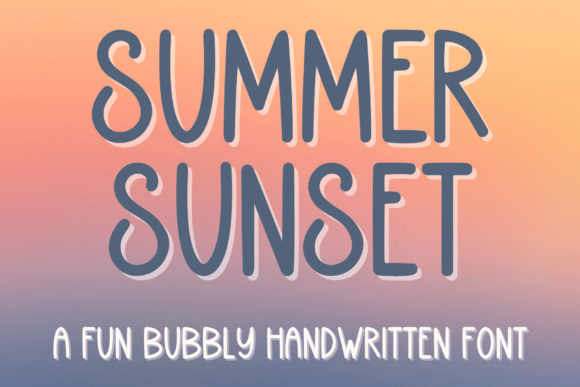
Summer Sunset
قد يكون العثور على عناصر التصميم المناسبة أمرًا صعبًا، ولكن Summer Sunset يقدم مجموعة استثنائية ترتقي بعملك على الفور.
سواء كنت تقوم بإنشاء منتجات الطباعة عند الطلب أو دعوات الزفاف أو رسومات وسائل التواصل الاجتماعي، فإن Summer Sunset هو الخيار المثالي.